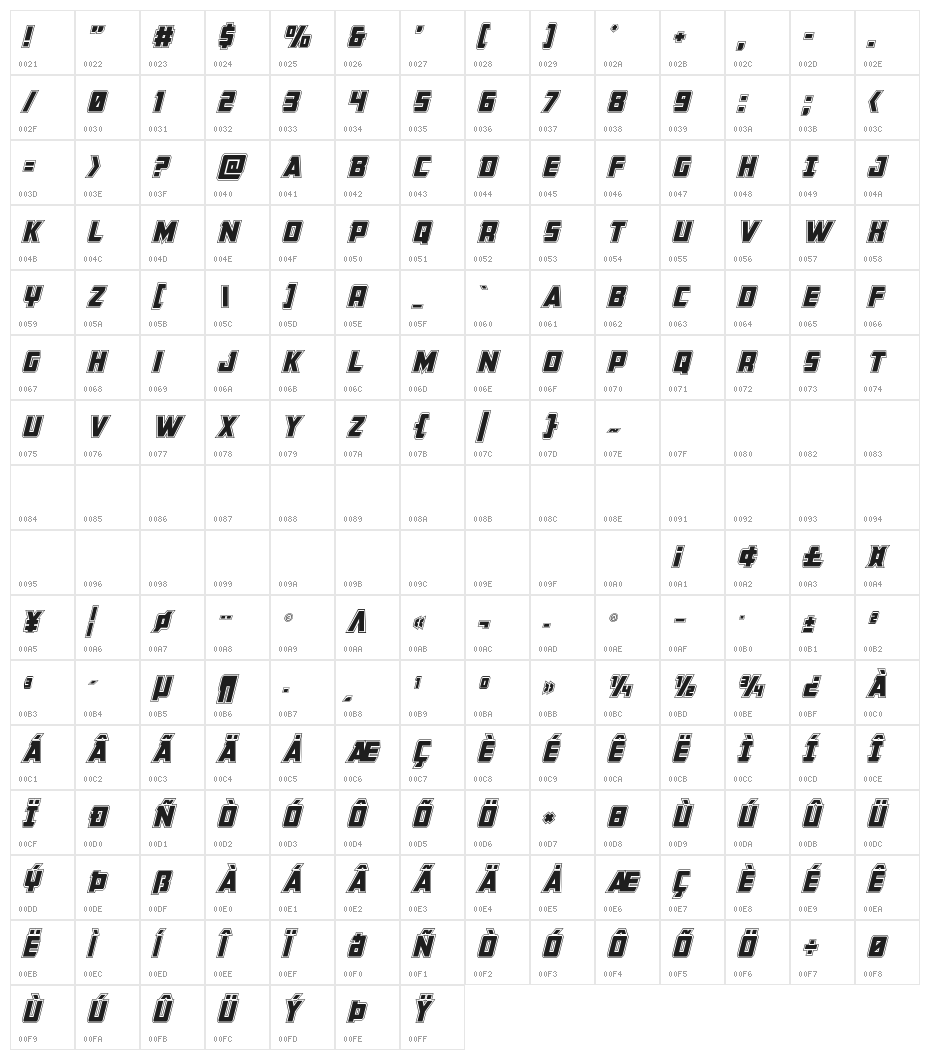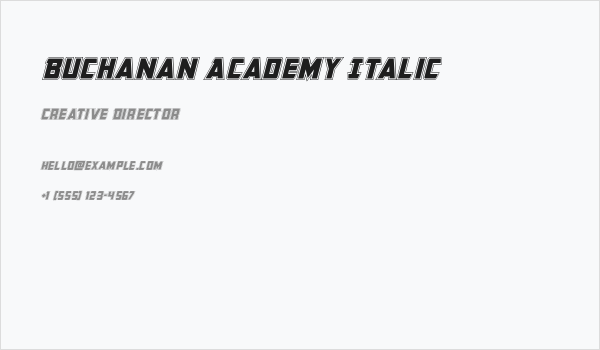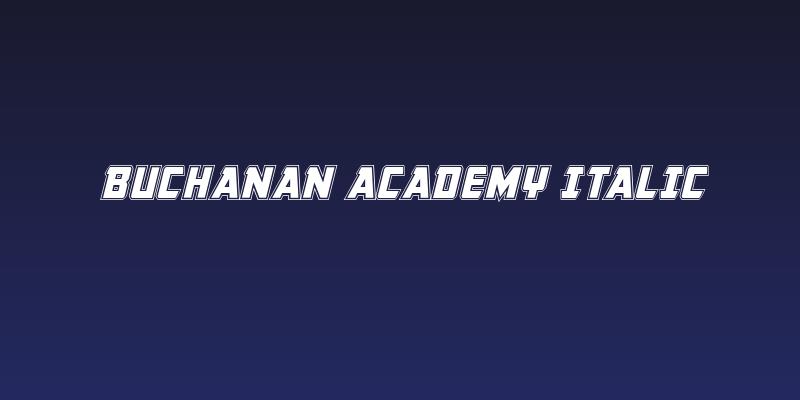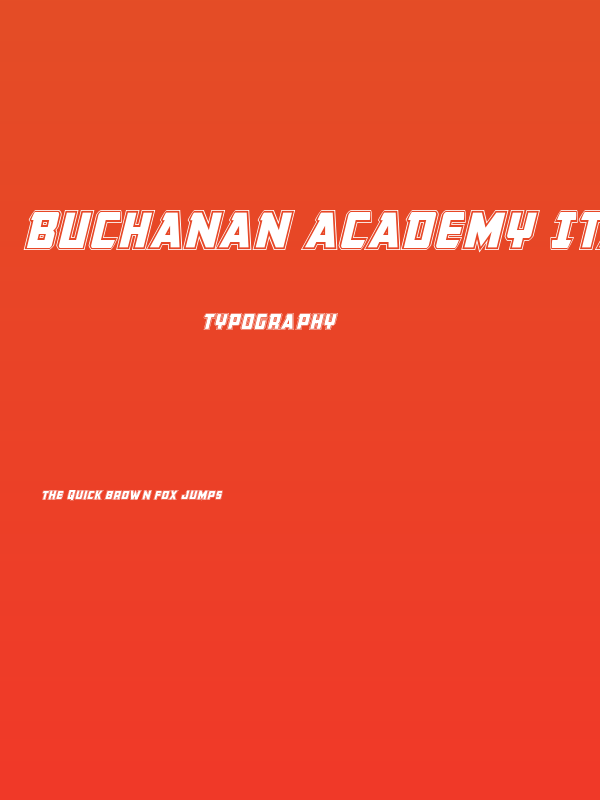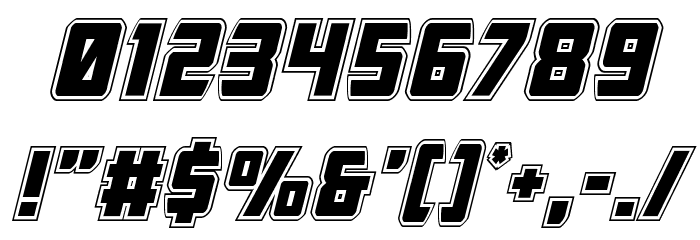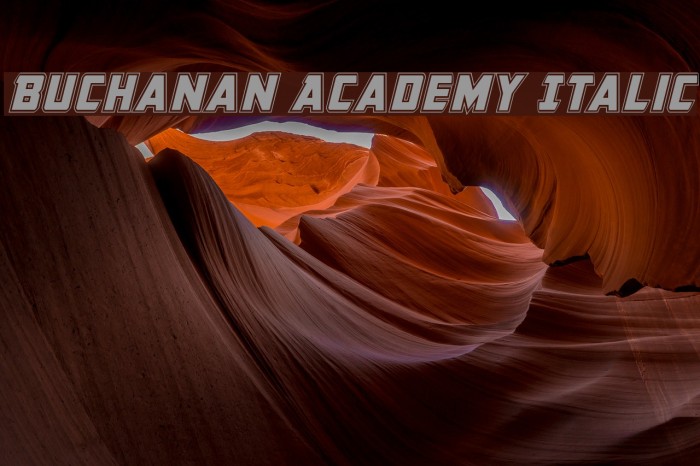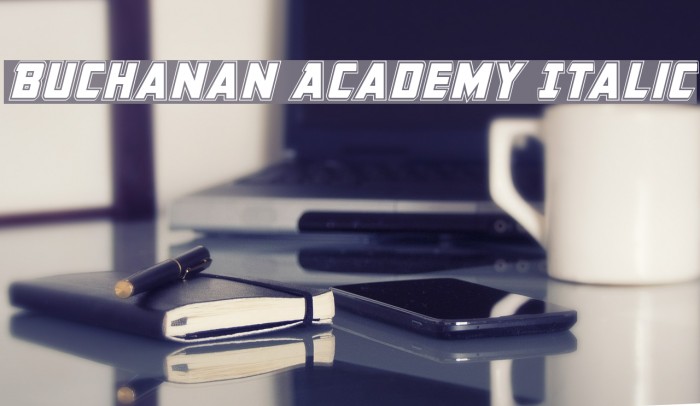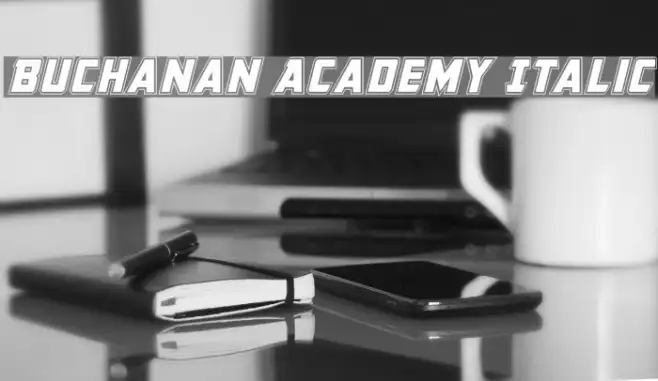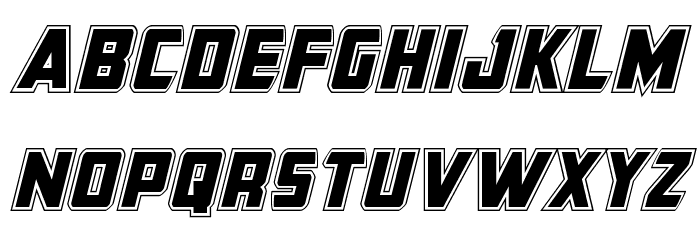
Buchanan Academy Italic Font
✎ Futuristic
| Vorgeschlagene Projekte | Ideal for sports branding, dynamic posters, modern logos, and eye-catching headlines. |